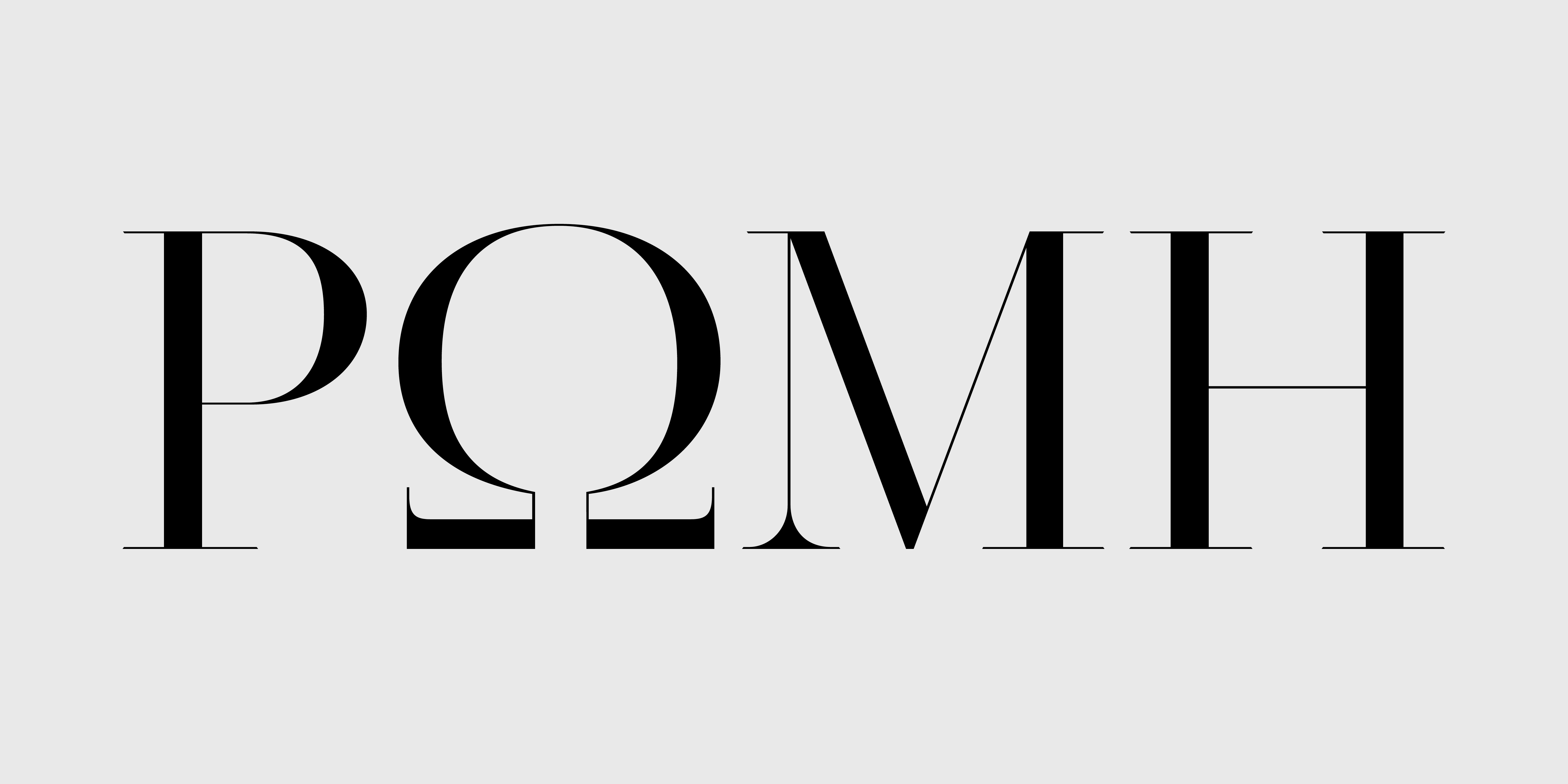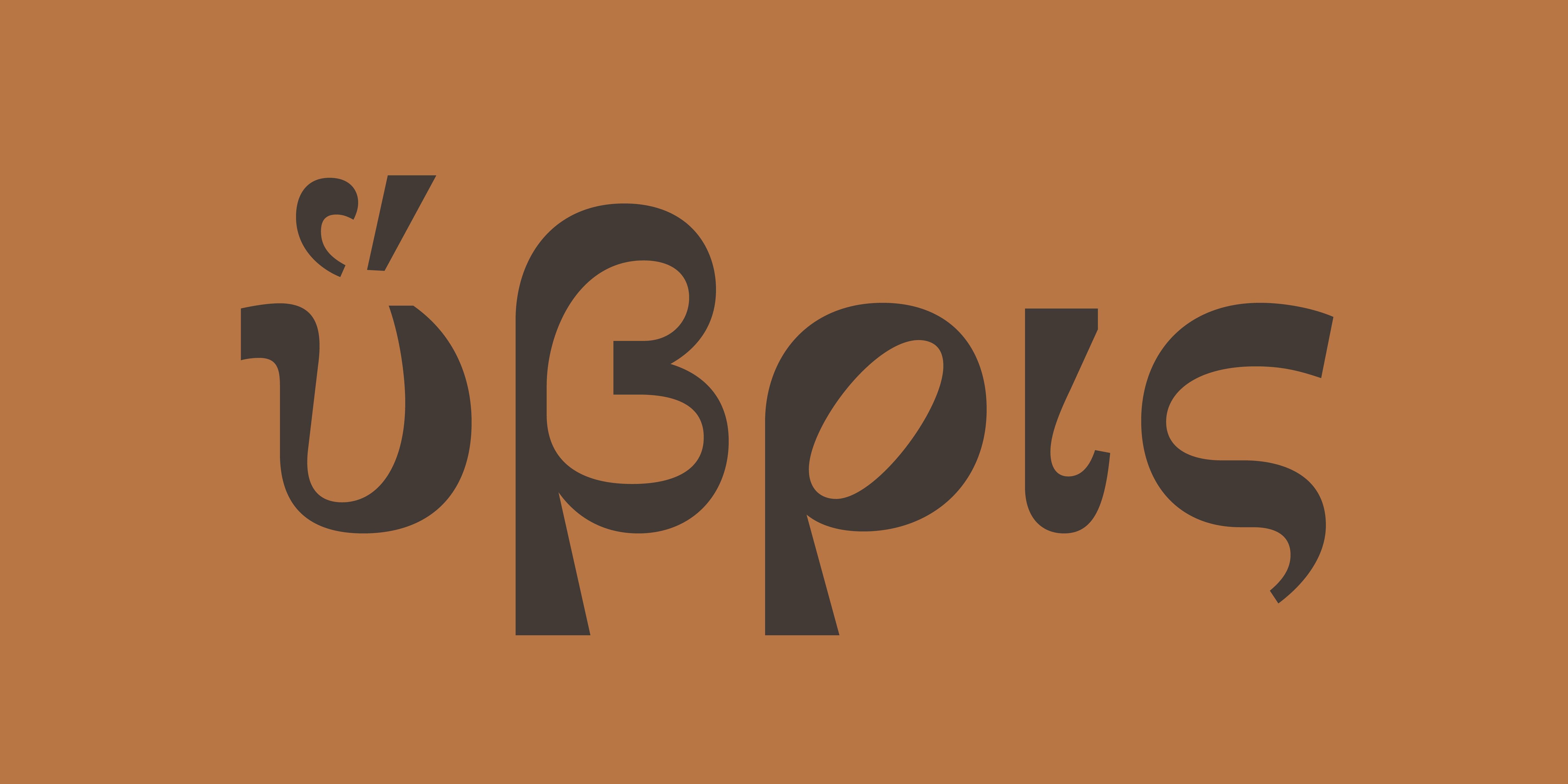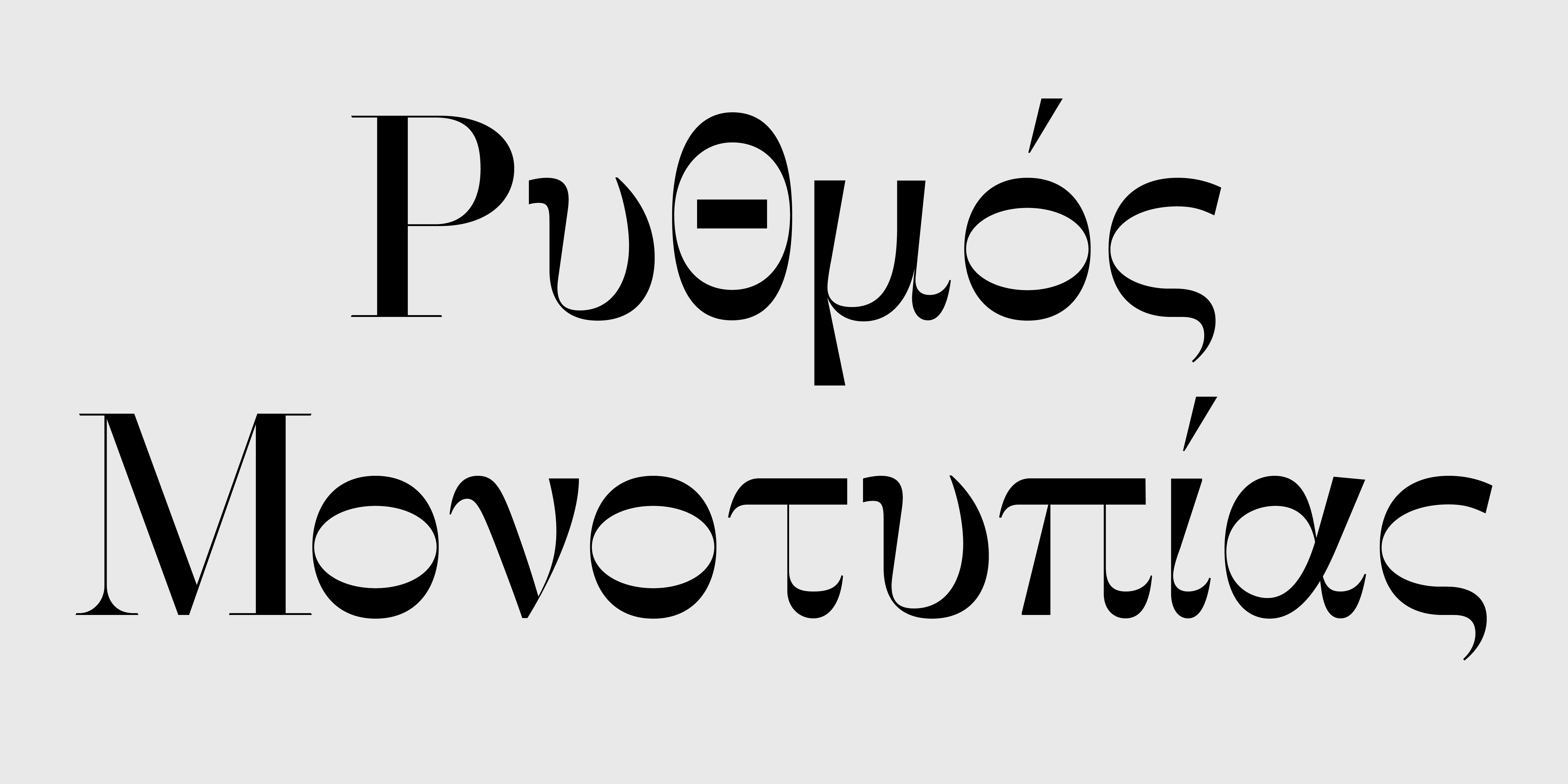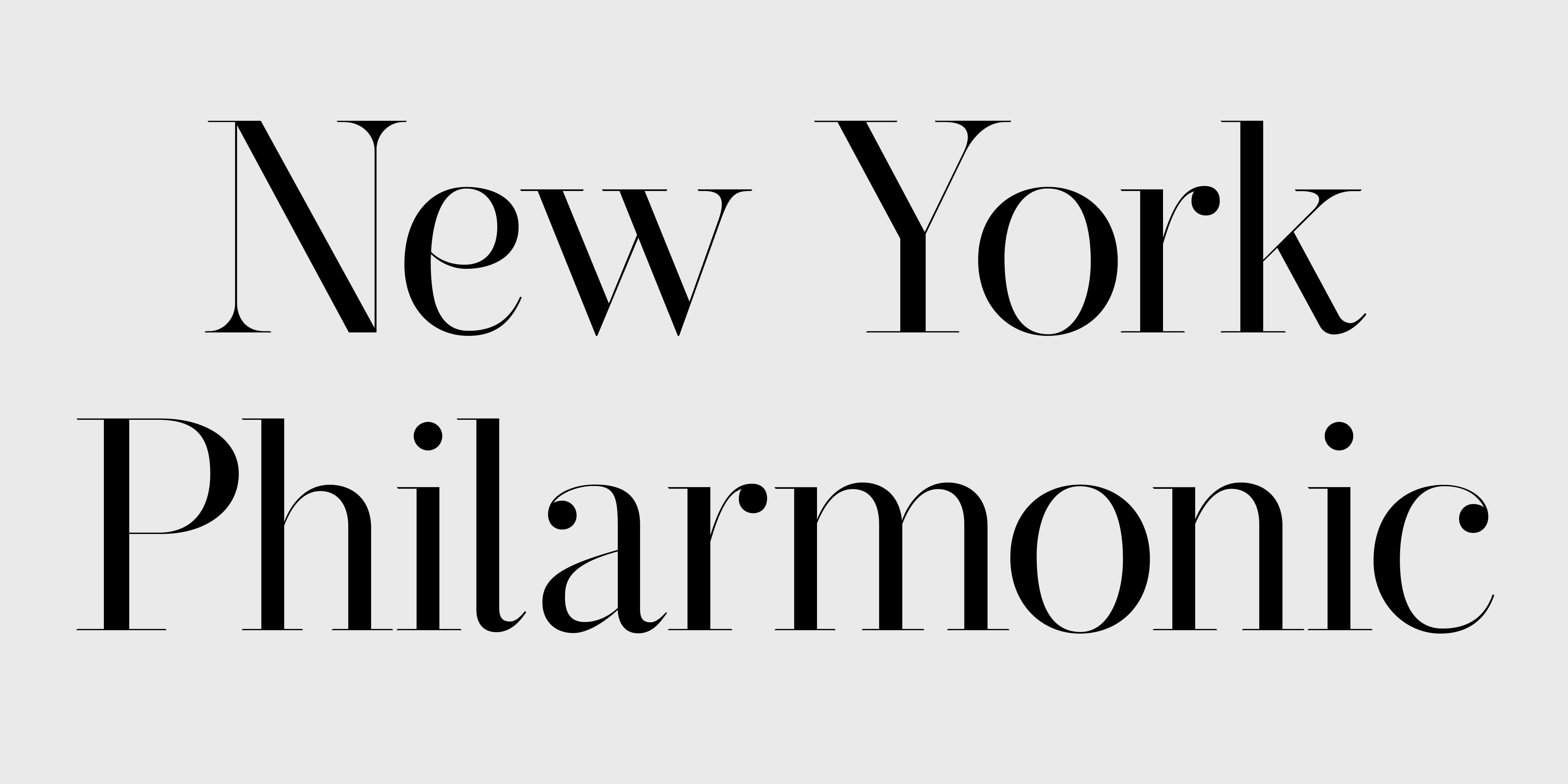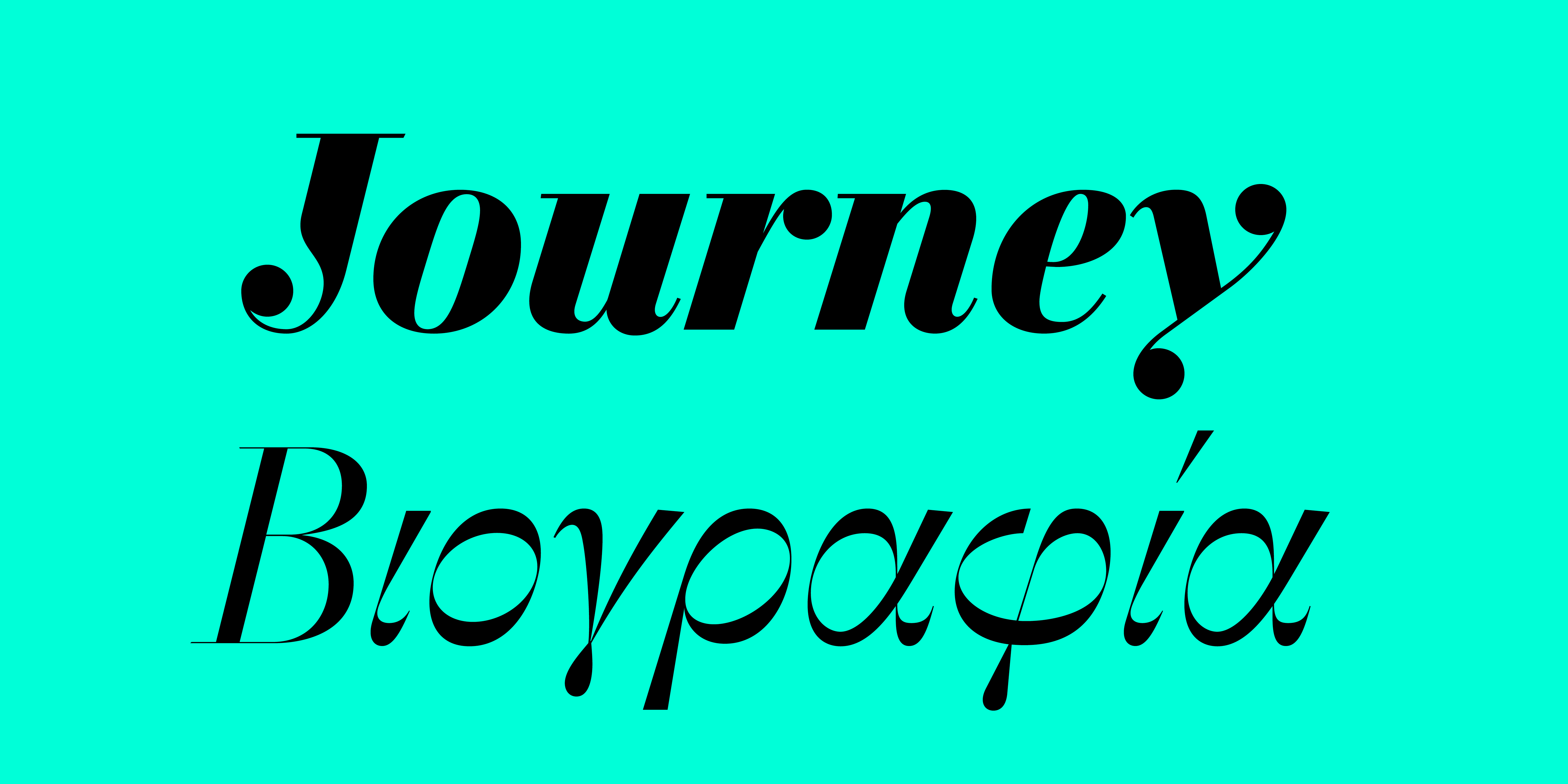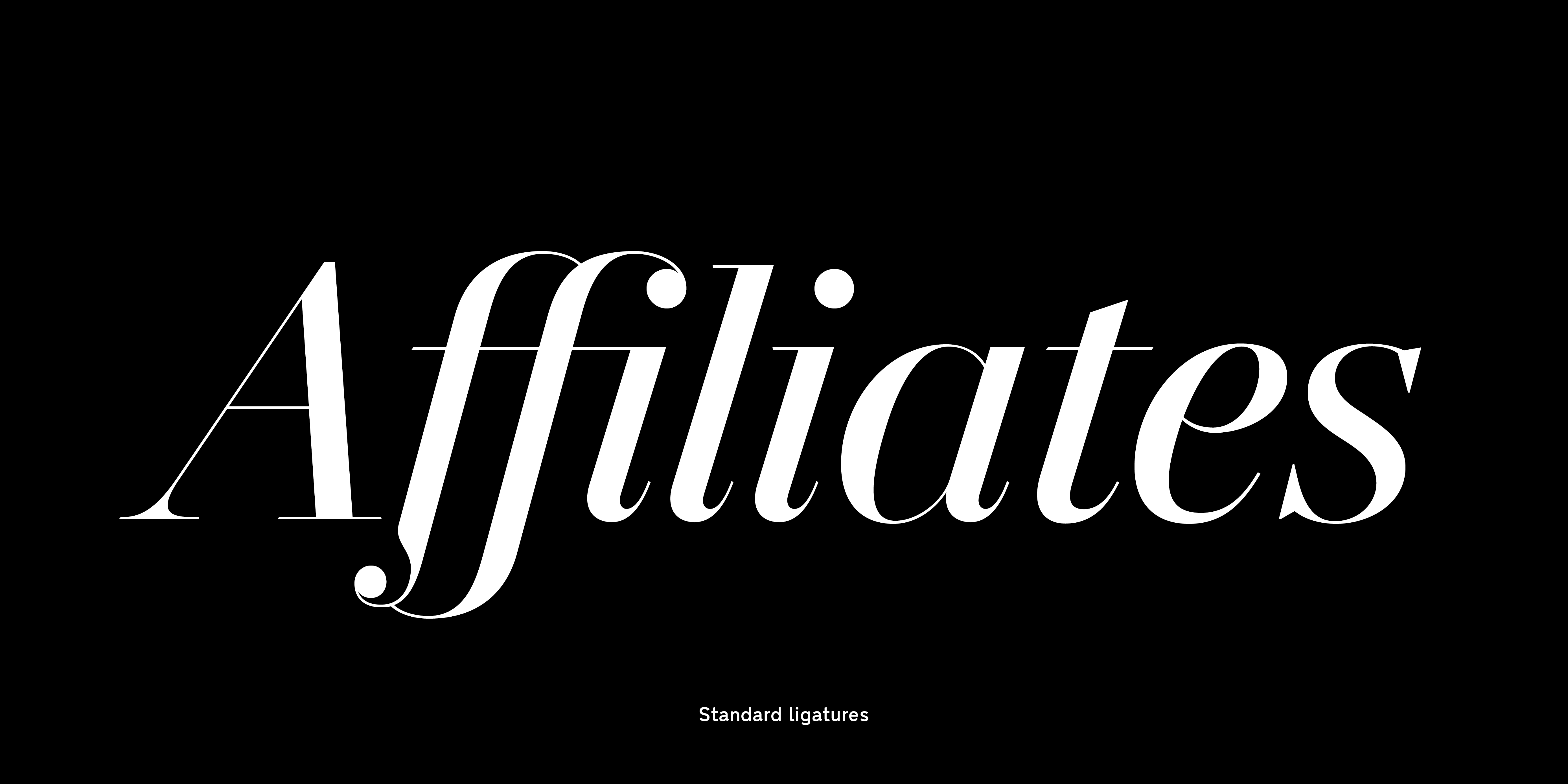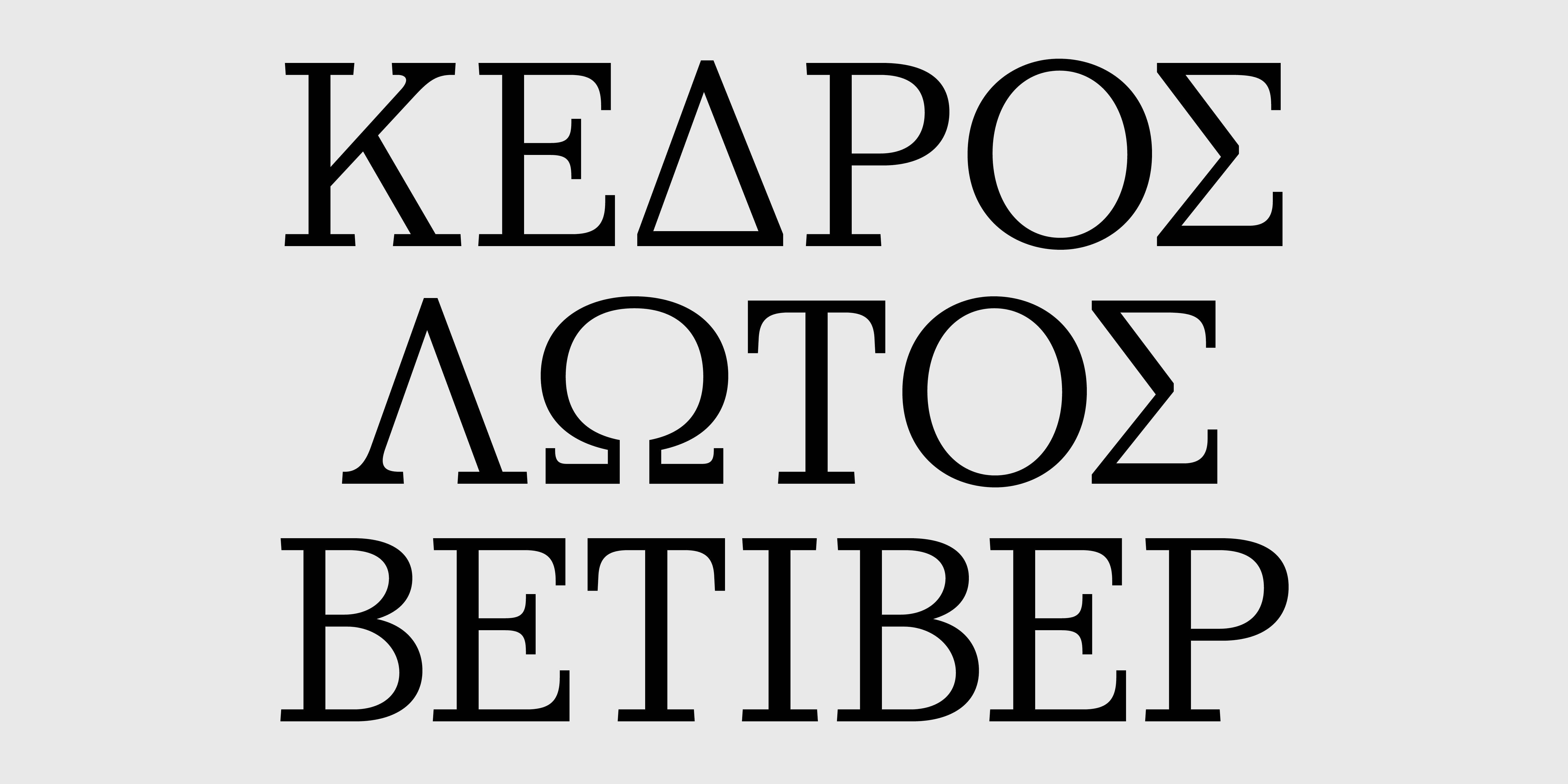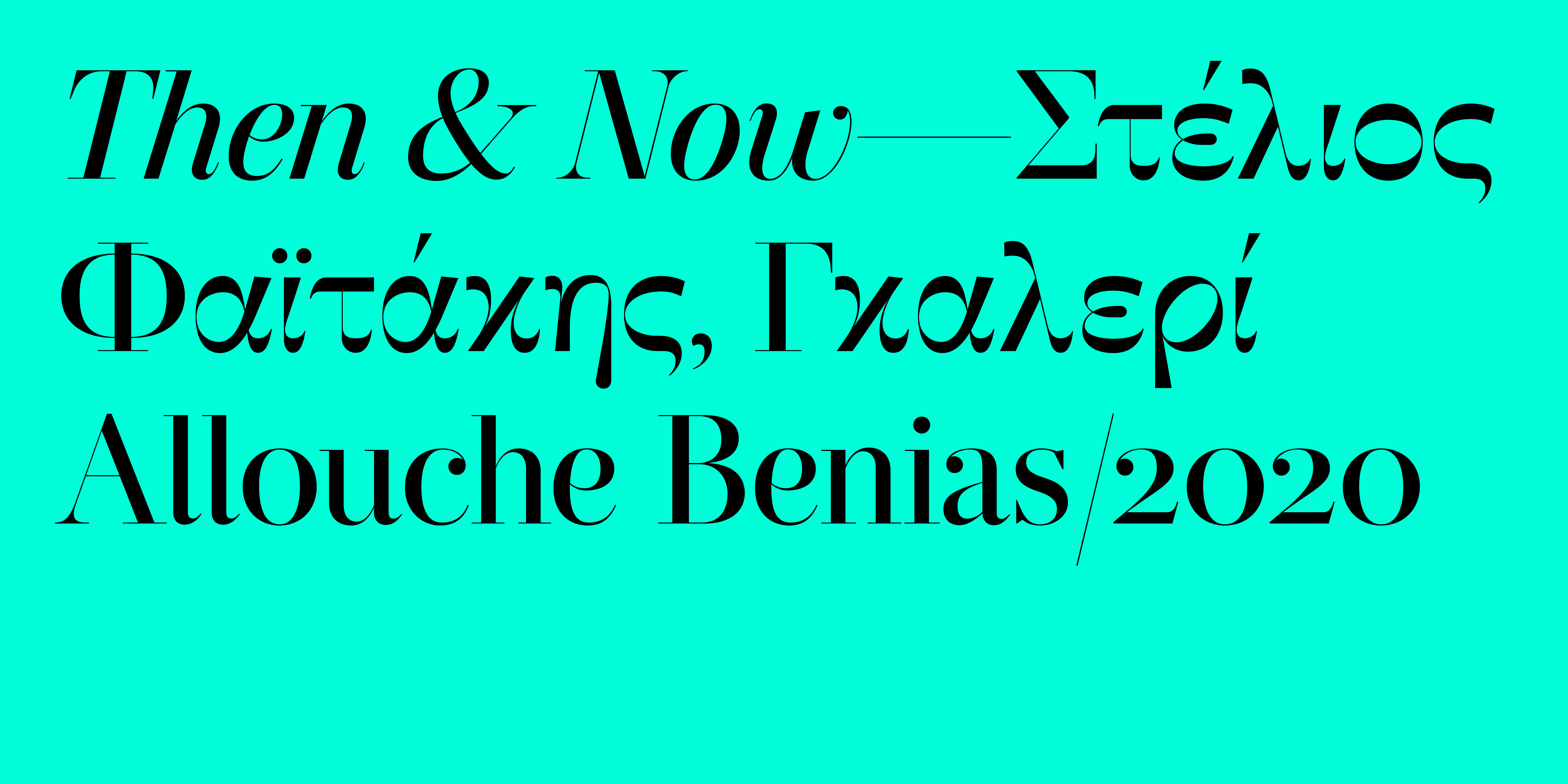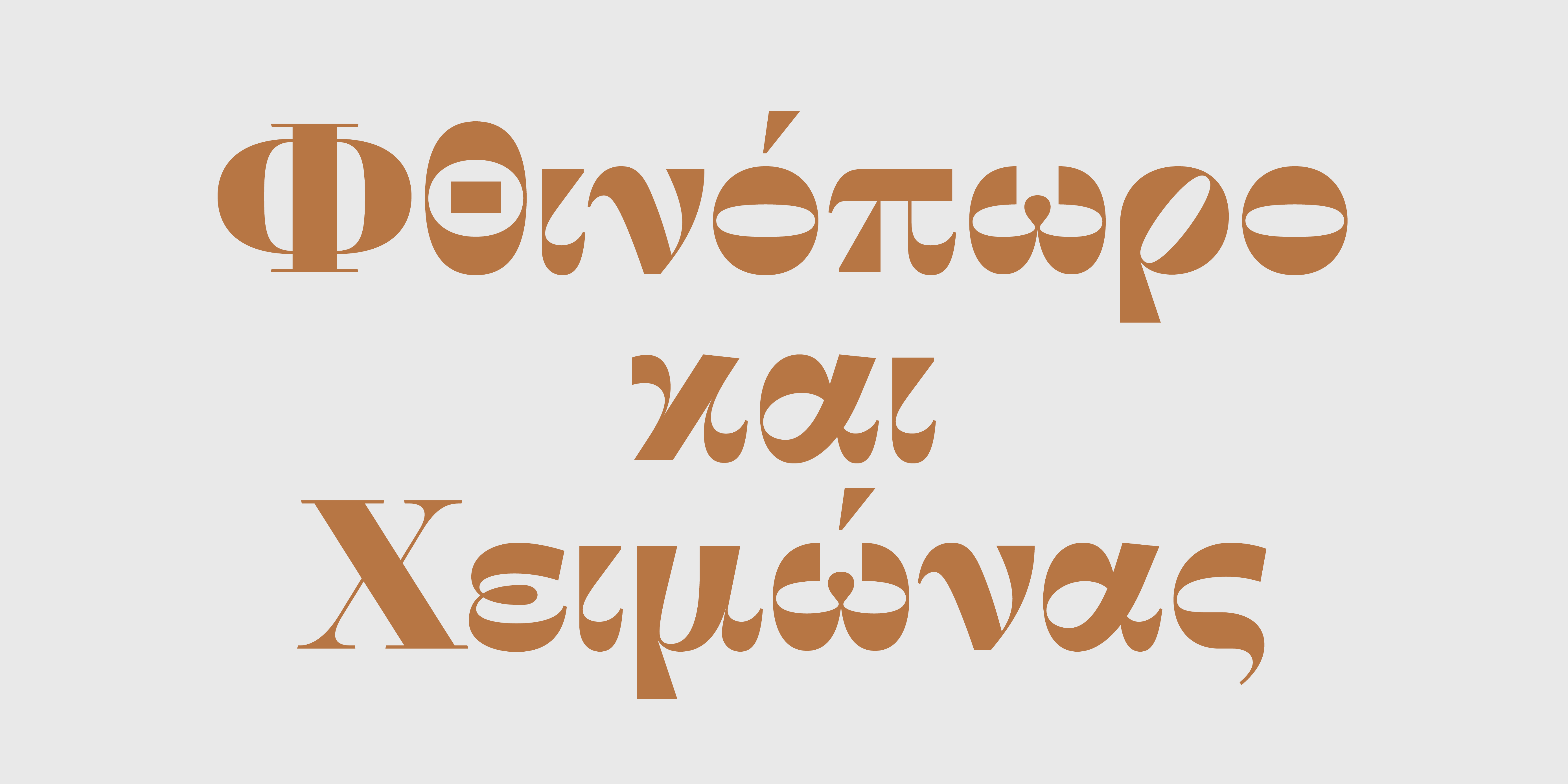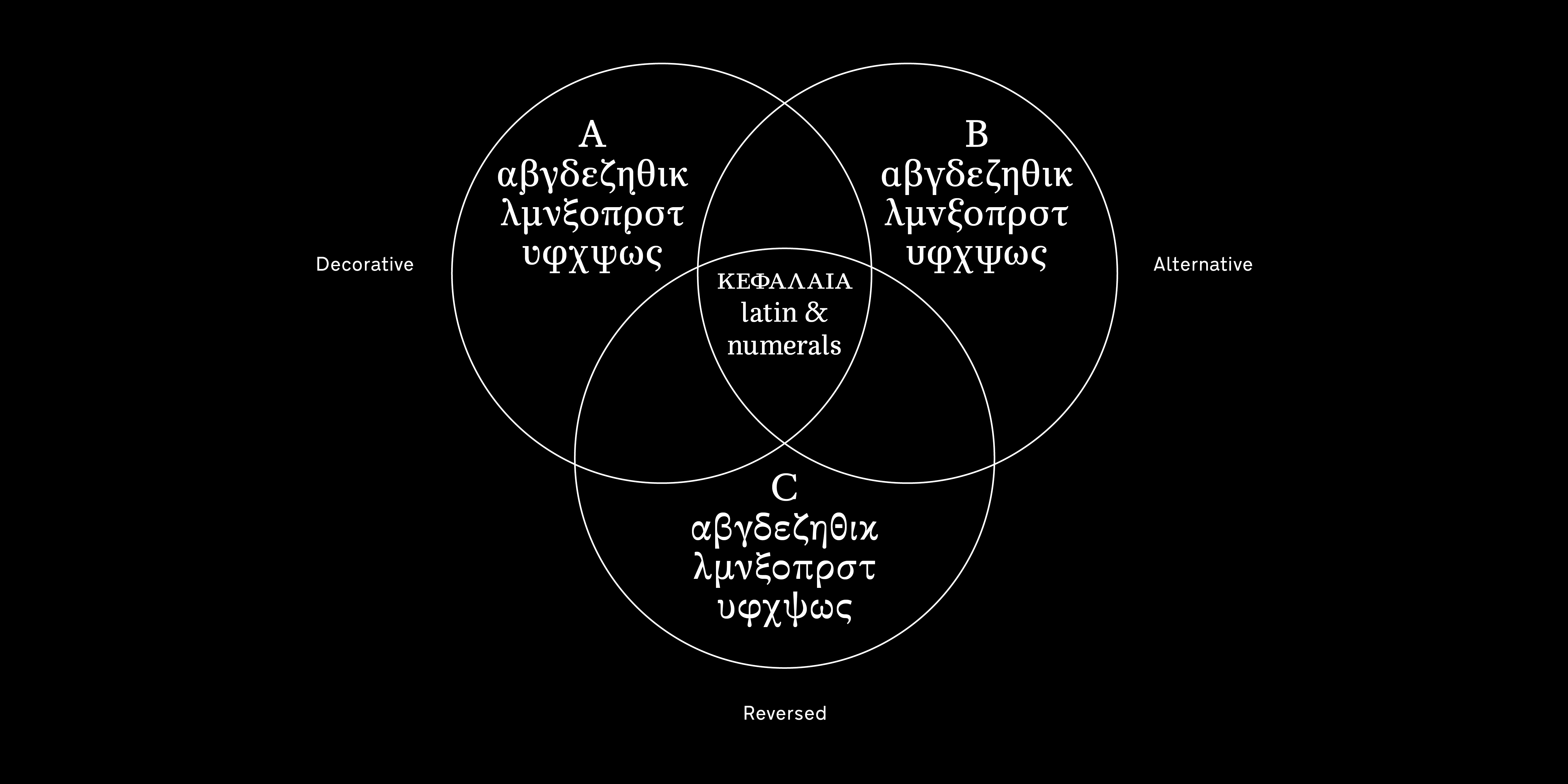
Ifigeneia Αντεστραμμένα
H CF Ifigeneia είναι μια πολυμορφική ανισόπαχη γραμματοσειρά που περιλαμβάνει τρεις διαφορετικές σχεδιαστικές προσεγγίσεις στα Ελληνικά. Την αρχική, που είναι μια Διακοσμητική προσέγγιση, την Εναλλακτική (alt) που ακολουθεί μια εκδοχή πιο κοντά στα λατινικά στοιχεία και την Αντεστραμμένη που παραπέμπει στα Απλά της Μονοτυπίας. Παράλληλα, διατίθεται σε δύο τύπους αντιθέσεων· υψηλού κοντράστ για χρήση σε τίτλους και μεγάλες στιγμές γραμμάτων και χαμηλού κοντράστ για χρήση σε κείμενα και μικρά μεγέθη.
Με βάση τα παραπάνω χαρακτηριστικά, η CF Ifigeneia μπορεί να χρησιμοποιηθεί σε κάθε εφαρμογή και για κάθε χρήση. Από την εταιρική ταυτότητα ενός ιδιαίτερου ξενοδοχείου (Διακοσμητική), την ιστοσελίδα ενός ειδησεογραφικού portal (Εναλλακτική), έως μία έντυπη ποιητική έκδοση σε πολυτονικό κείμενο (Αντεστραμμένα).
Η CF Ifigeneia αρχικά σχεδιάστηκε στο βάρος Light το 2004-05 για ένα έντυπο περιοδικό μόδας. Η γραμματοσειρά ξανασχεδιάστηκε, προστέθηκαν νέα βάρη και πλάγιοι χαρακτήρες και κυκλοφόρησε είκοσι περίπου χρόνια μετά την πρώτη της παρουσίαση.